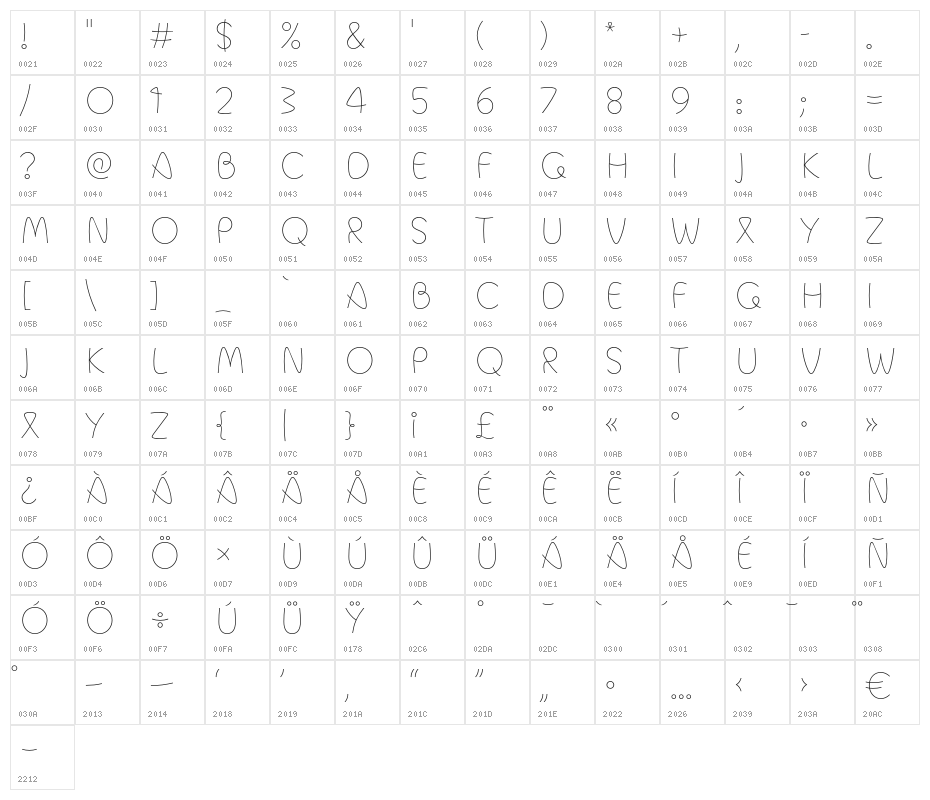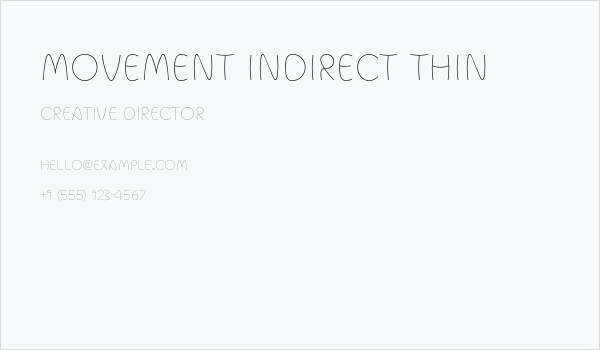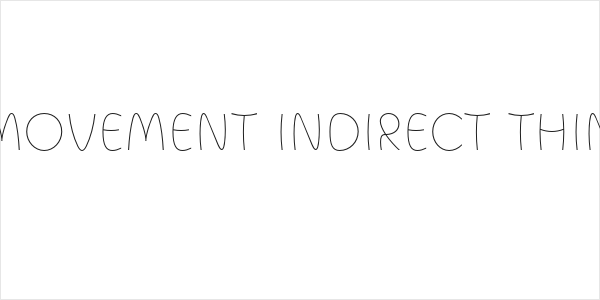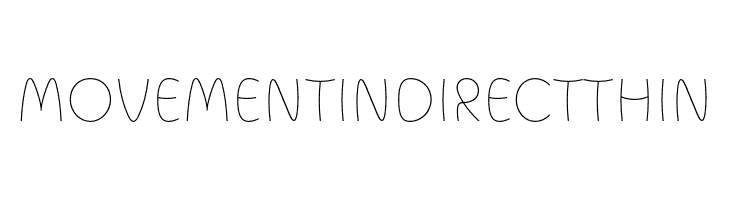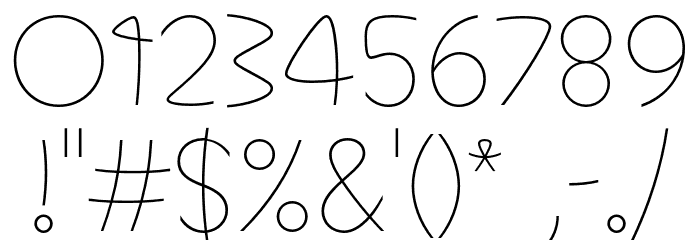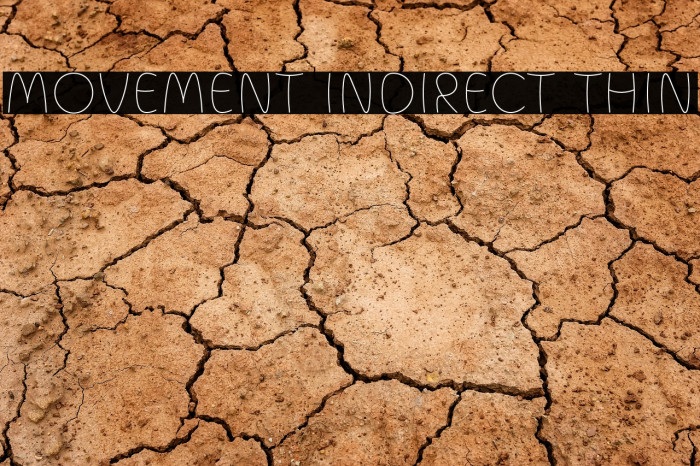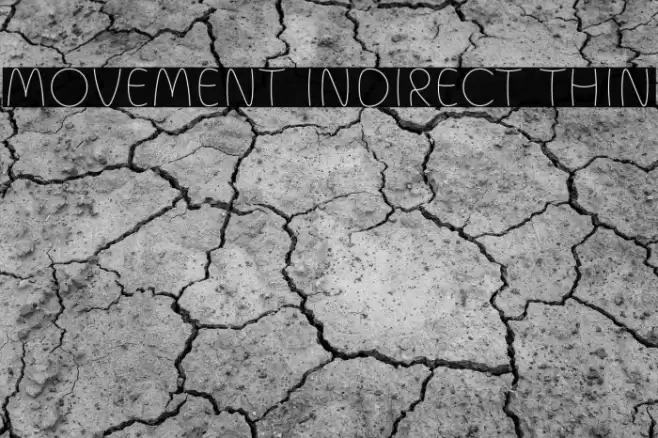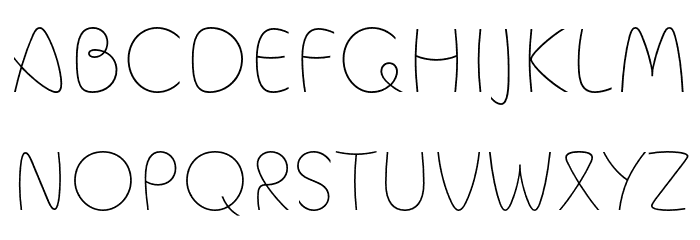
Movement Indirect Thin Font
| Общий стиль | Playful, Whimsical |
| Область применения | Headlines, Creative projects |
| Рекомендуемые проекты | Ideal for creative projects such as invitations, greeting cards, and playful branding materials. |